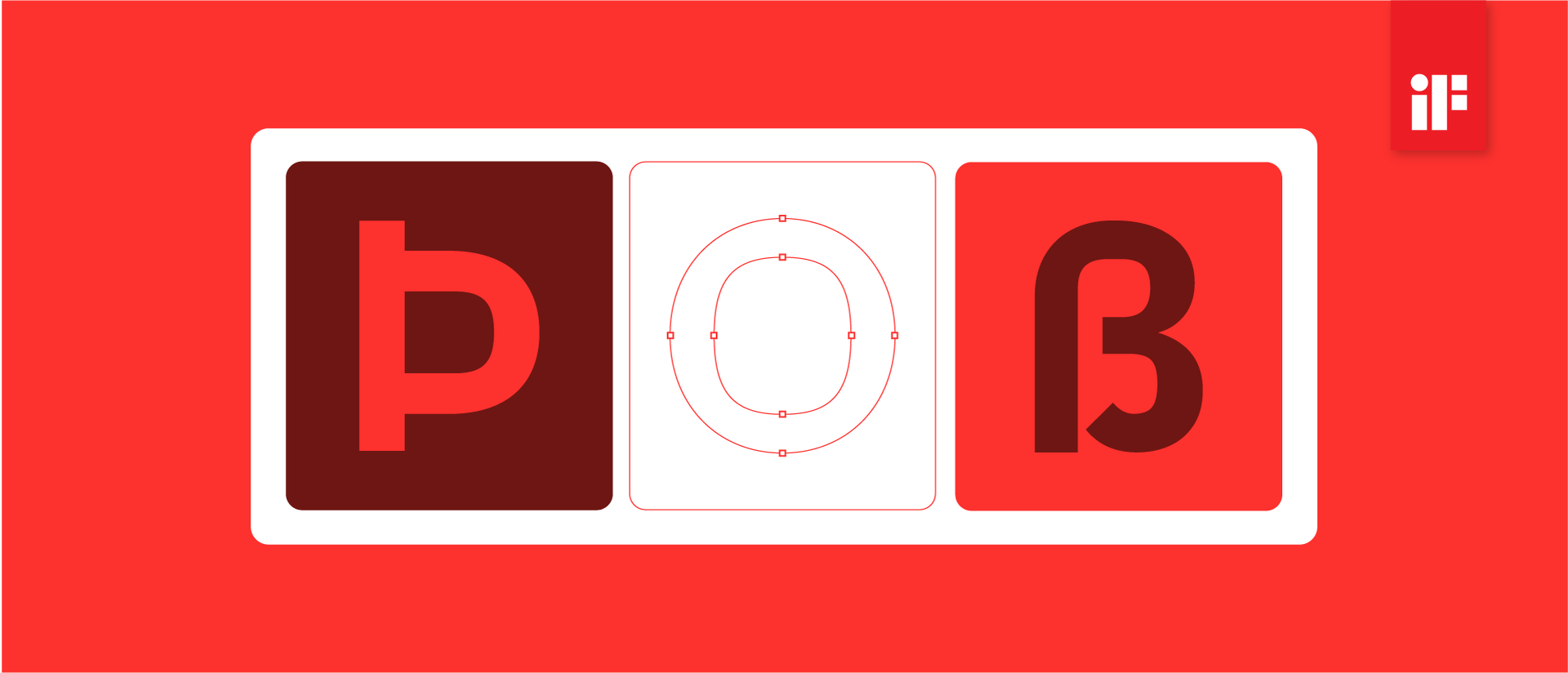
LG EI Headline
「LG EI Headline」은 ‘LG전자’의 웹과 앱 등의 환경을 고려하여 제작된 폰트 패밀리입니다.
글로벌 활용을 목적으로 라틴, 라틴 확장, 그릭, 베트남 문자를 제작했습니다. 글로벌 사용자의 니즈와 목적에 맞는 글립을 구성하고 이에 최적화된 형태로 디자인했습니다.
‘LG’의 디자인 철학인 ‘Emotionally Intelligent’을 바탕으로 디자인되었으며, 내외부가 상반되는 아웃라인의 형태를 통해 기하학인 인상으로 설계되었습니다. 외부의 원은 혁신적인 기술을, 내부의 둥근 모서리는 따뜻함과 감성을 상징합니다.
WeightThin, Light, Regular, SemiBold, Bold, Variable
라틴 95/ 확장 라틴(베트남어 포함) 427/ 그릭 74